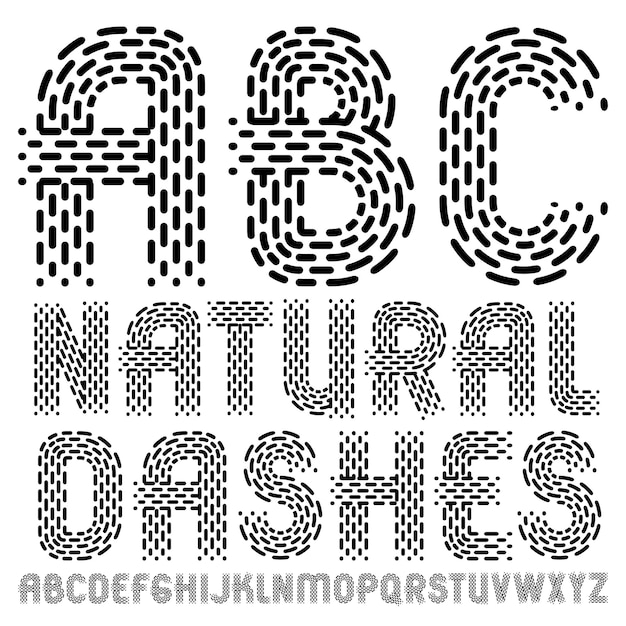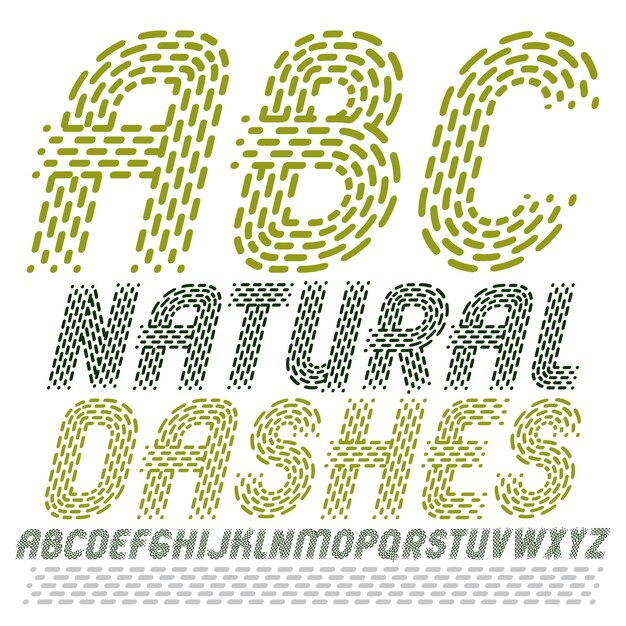
Векторные элегантные прописные буквы английского алфавита, коллекция abc. Округлый полужирный шрифт, шрифт от а до я может использоваться в дизайне ретро-плаката. Выполнен параллельными пунктирными линиями.Векторные элегантные прописные буквы английского алфавита, коллекция abc. Округлый полужирный шрифт, шрифт от а до я может использоваться в дизайне ретро-плаката. Выполнен параллельными пунктирными линиями.
Векторные элегантные прописные буквы английского алфавита, коллекция abc. Округлый полужирный шрифт, шрифт от а до я может использоваться в дизайне ретро-плаката. Выполнен параллельными пунктирными линиями.